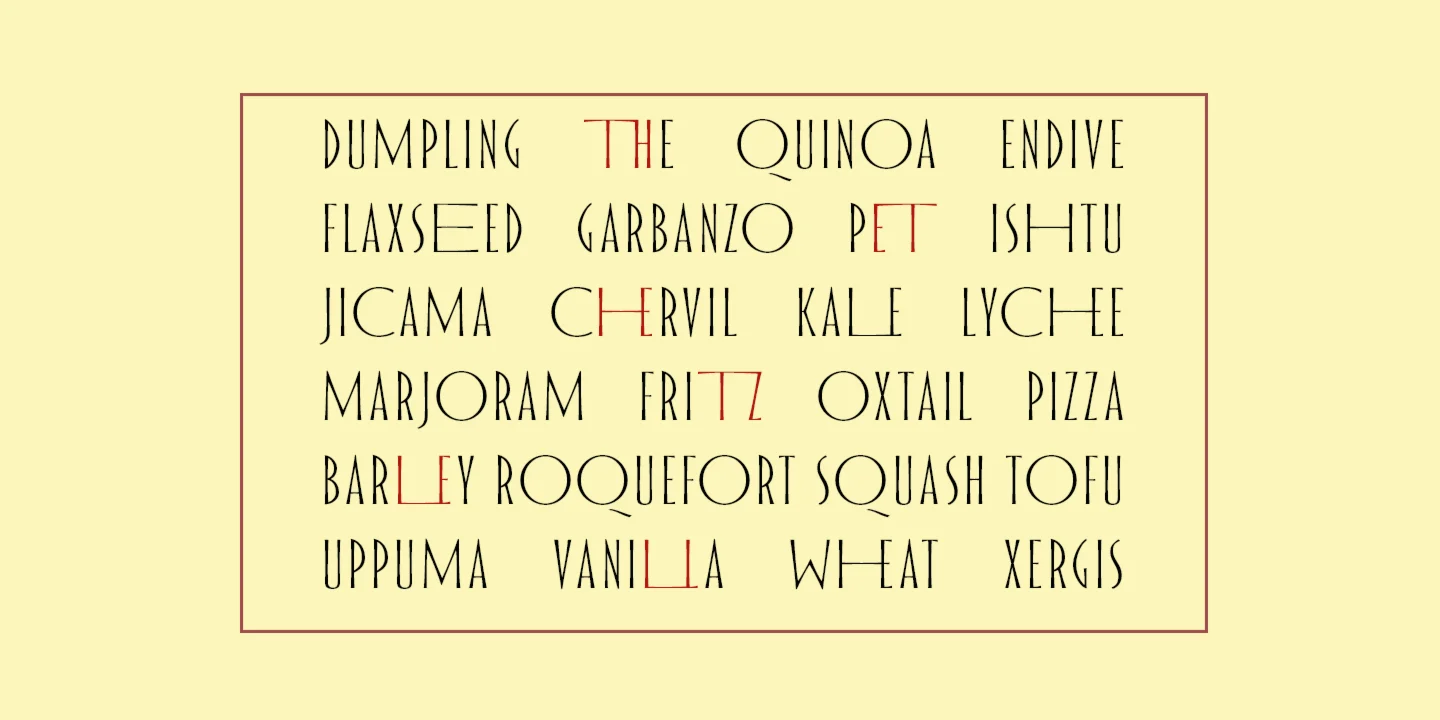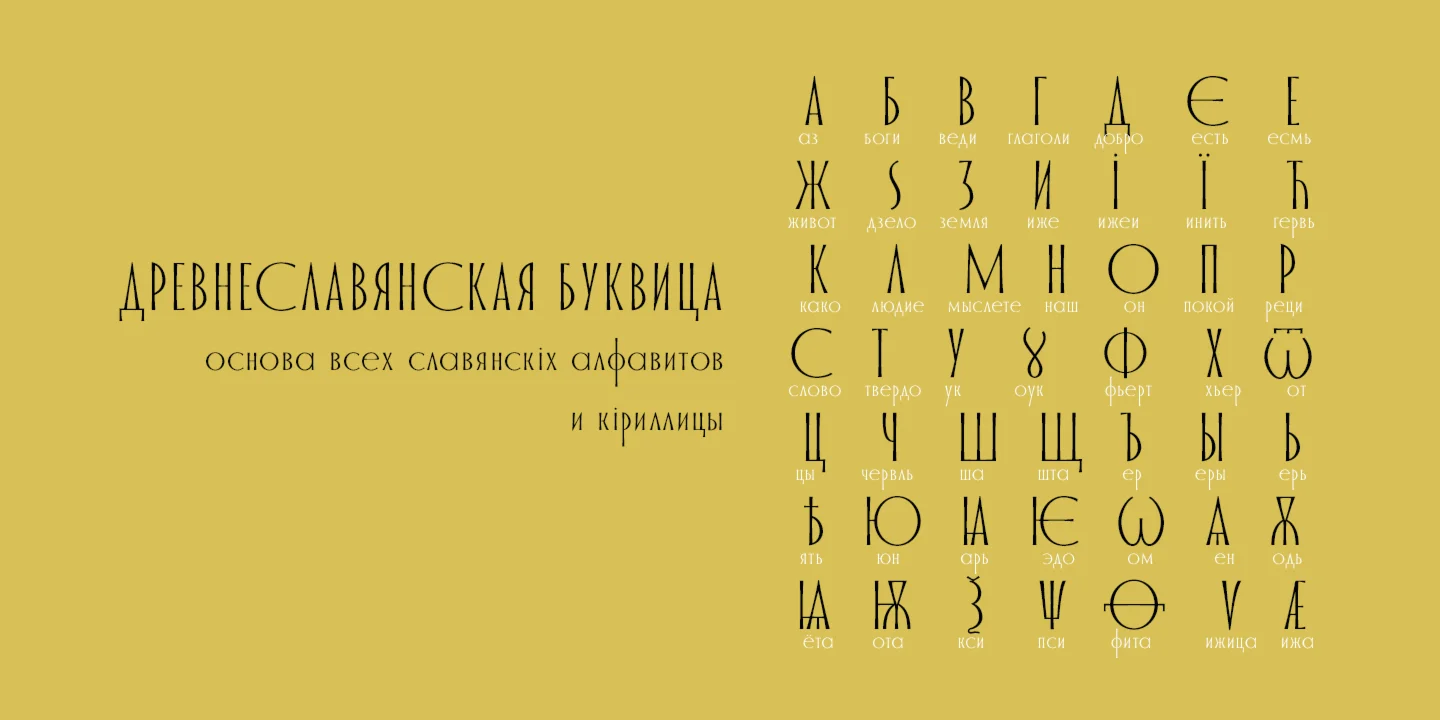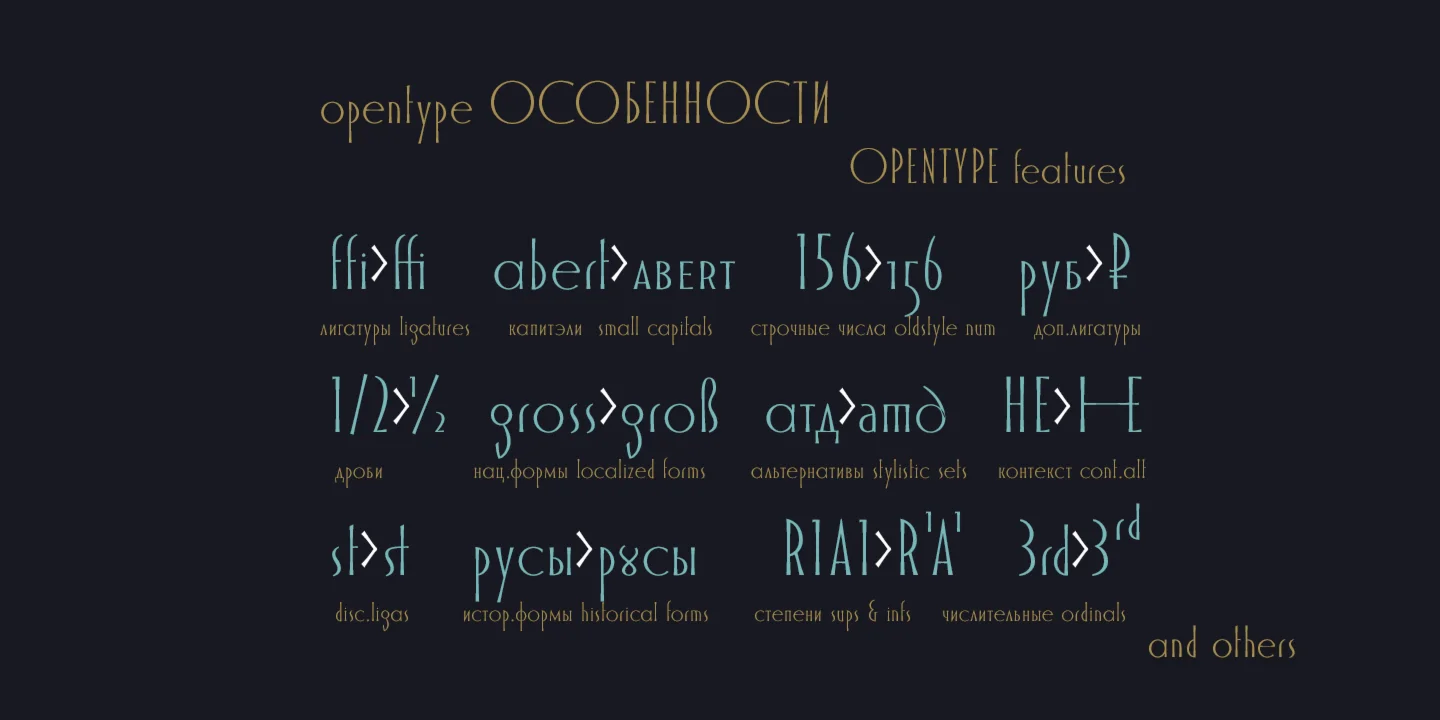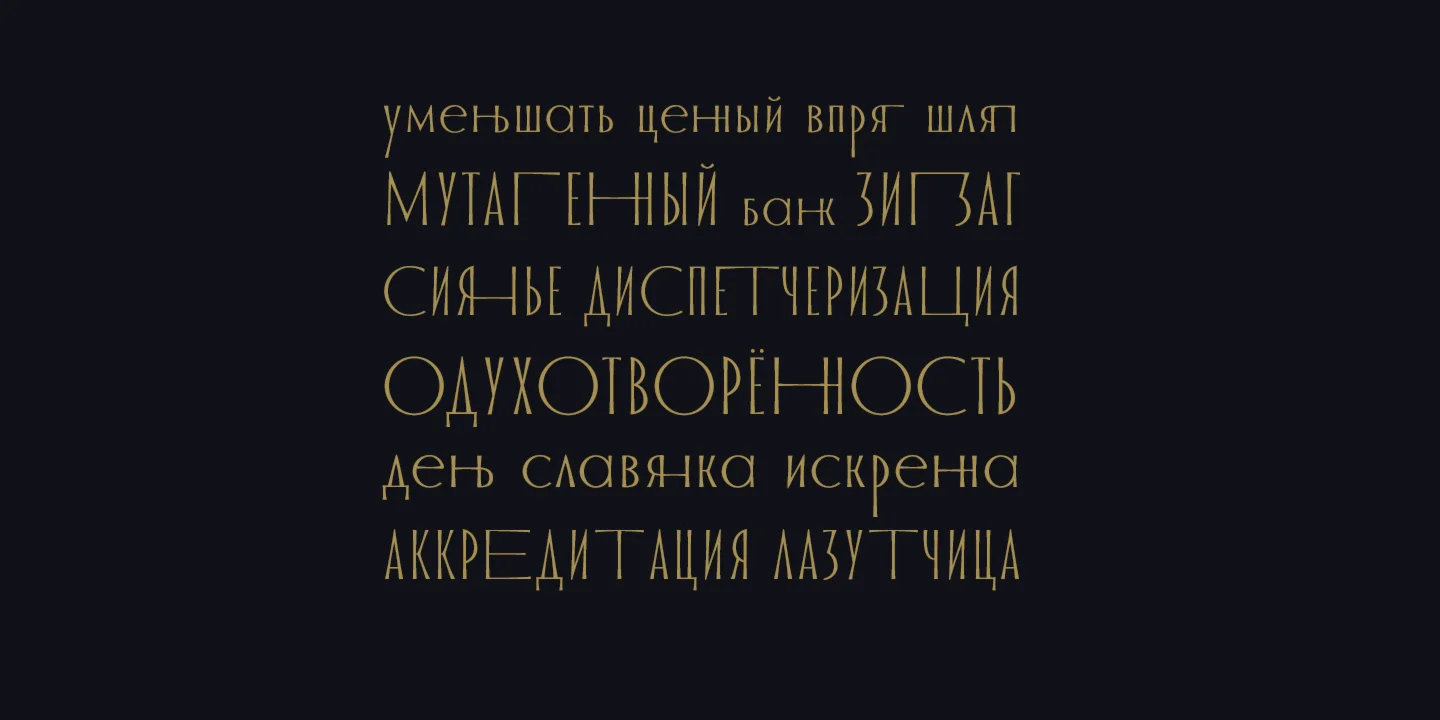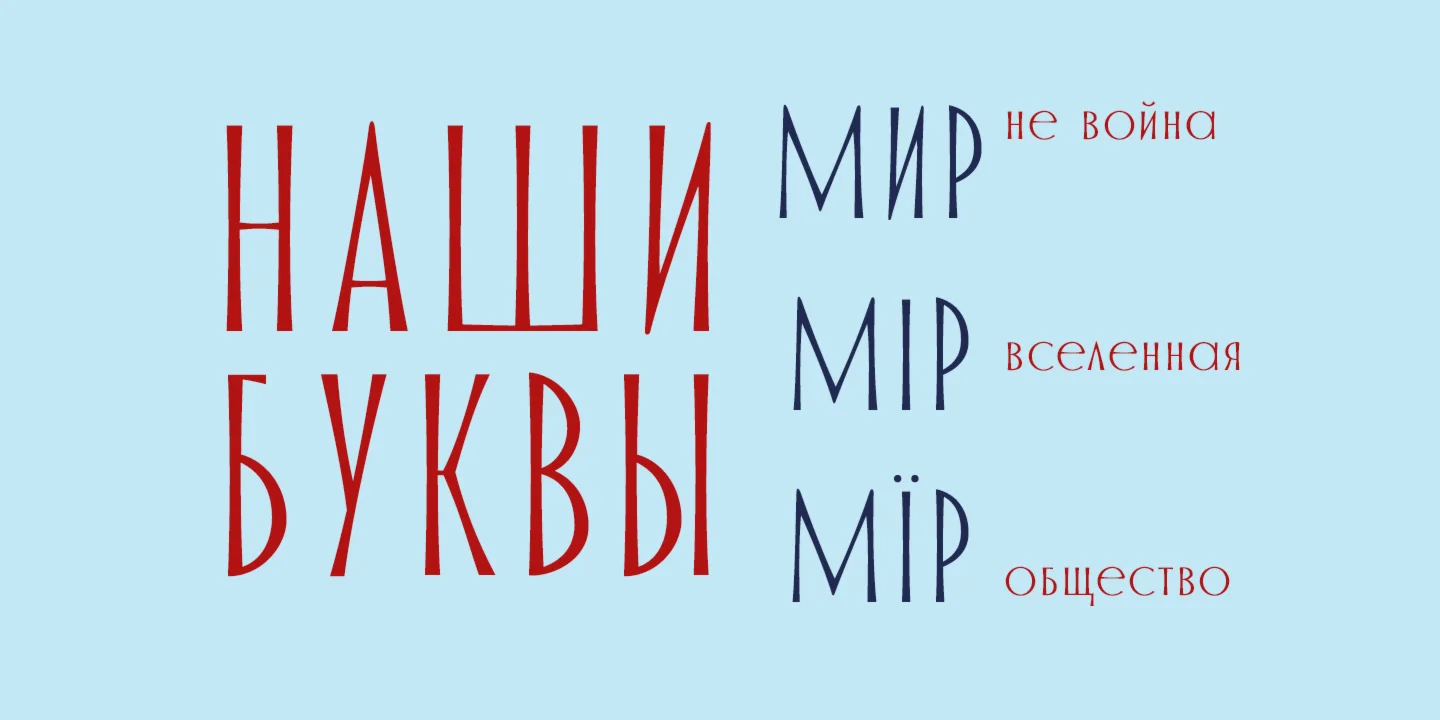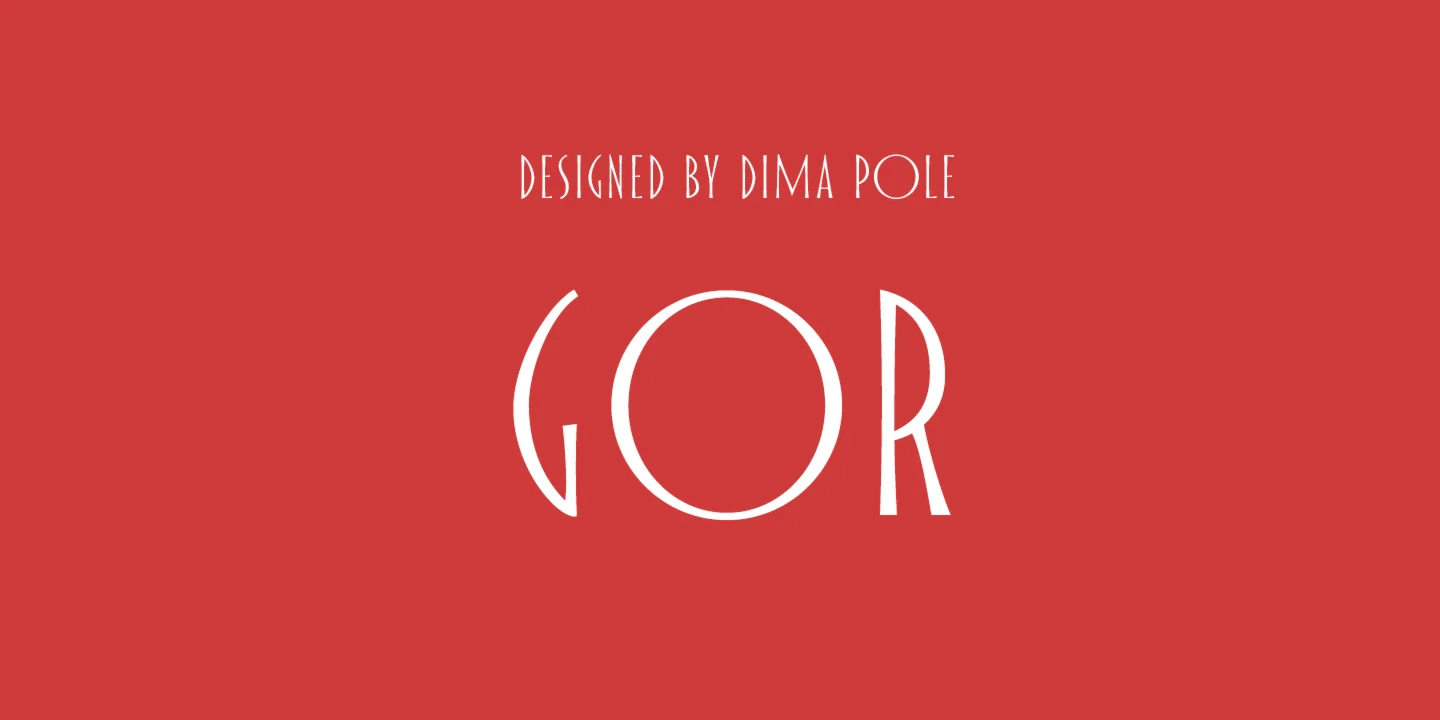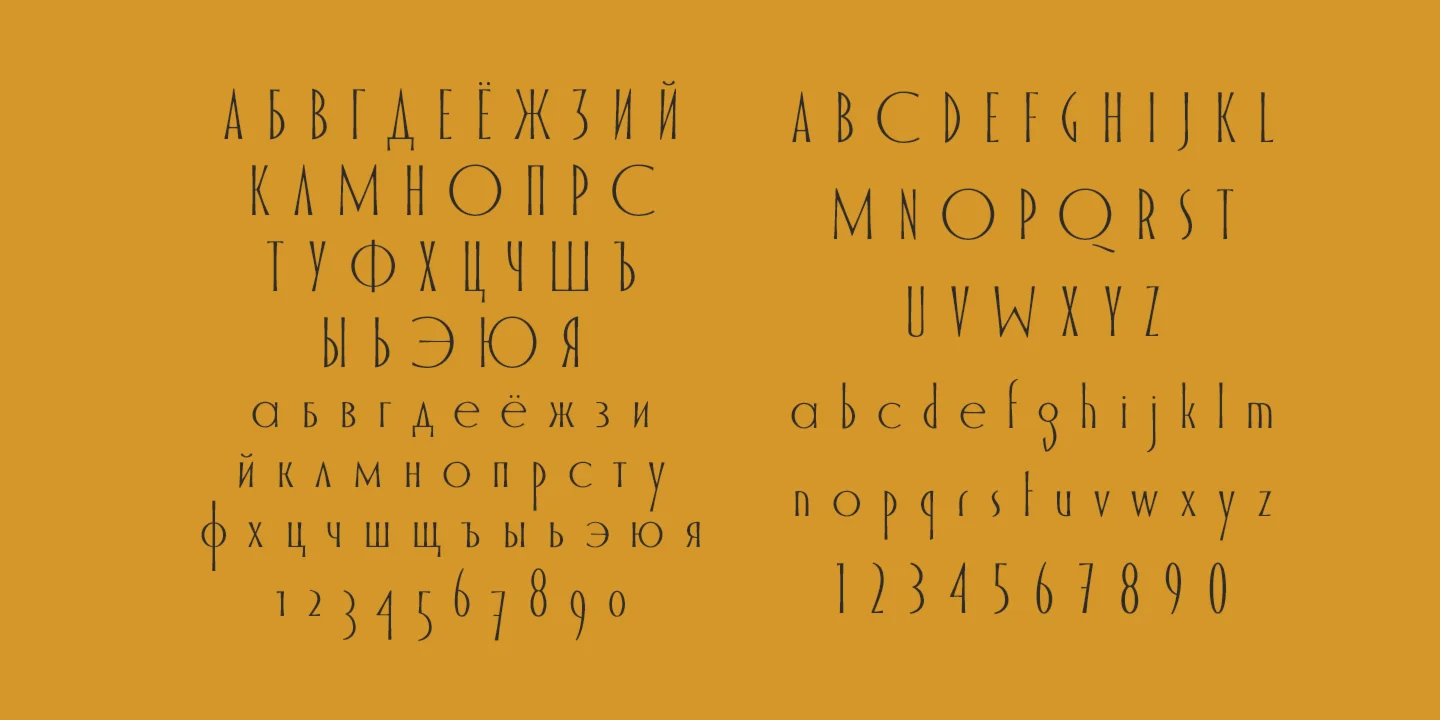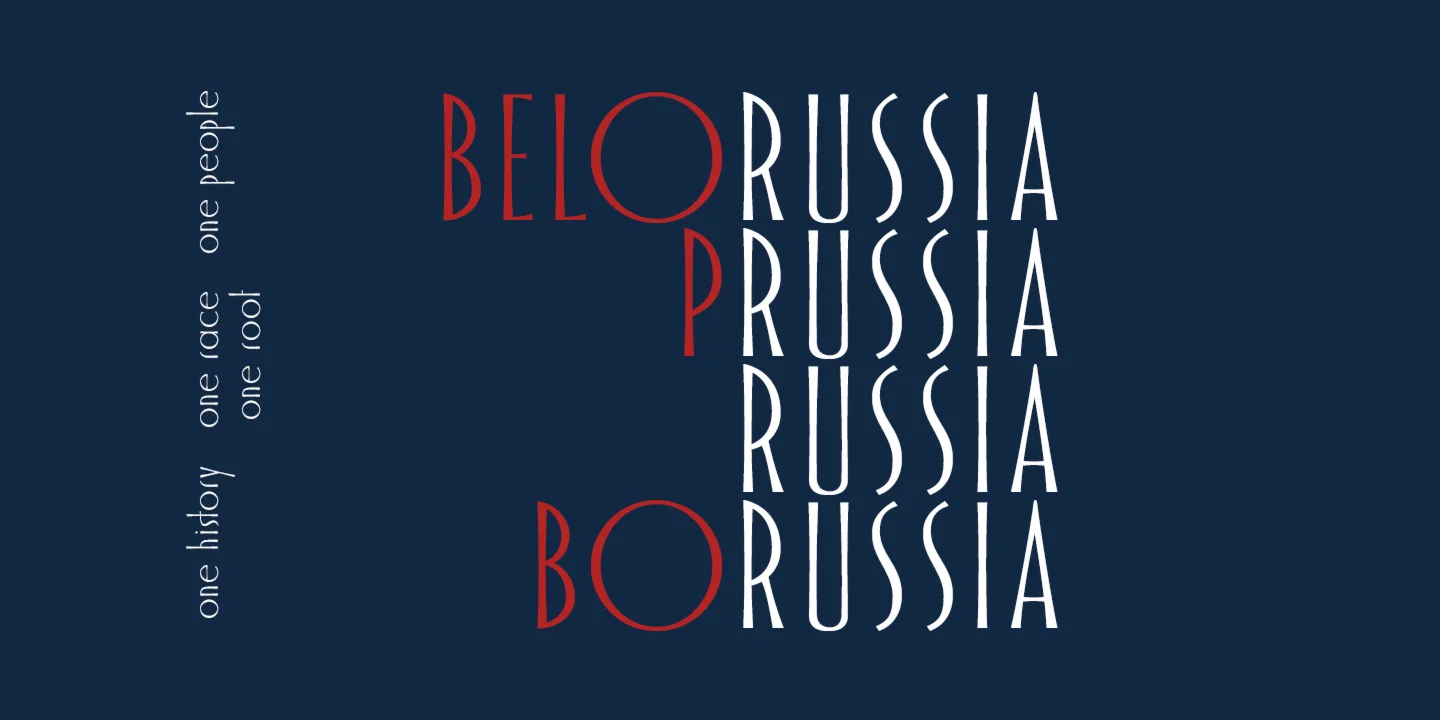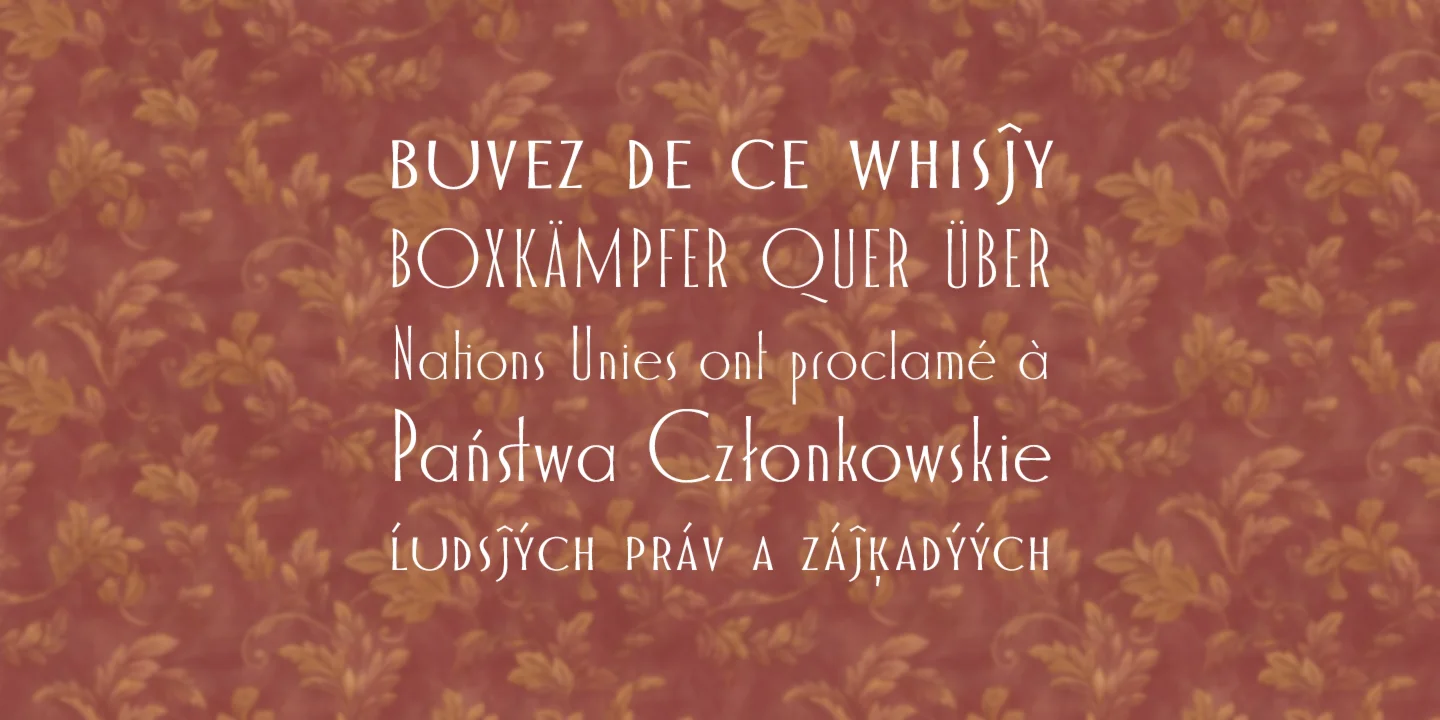
Шрифт ГОР родился из одной буквы) Он имеет изящную форму линий и приятные пропорции. Особый шарм шрифту придаёт сочетание узких букв и широких округлых букв, что создаёт живой и оригинальный характер. Особо интересное решение это буквы-связи (лигатуры), составленные из характерных букв шрифта, что в тексте смотрится шикарно, придавая особую изюминку (контекстуальные лигатуры).
ГОР включает все буквы Славянских и Европейских алфавитов, обычные и строчные числа, капитэли, всего около 1000 символов, а также 29 ОТ-особенностей (Opentype features), благодаяр чему его можно использовать в совершенно различных ситуациях.